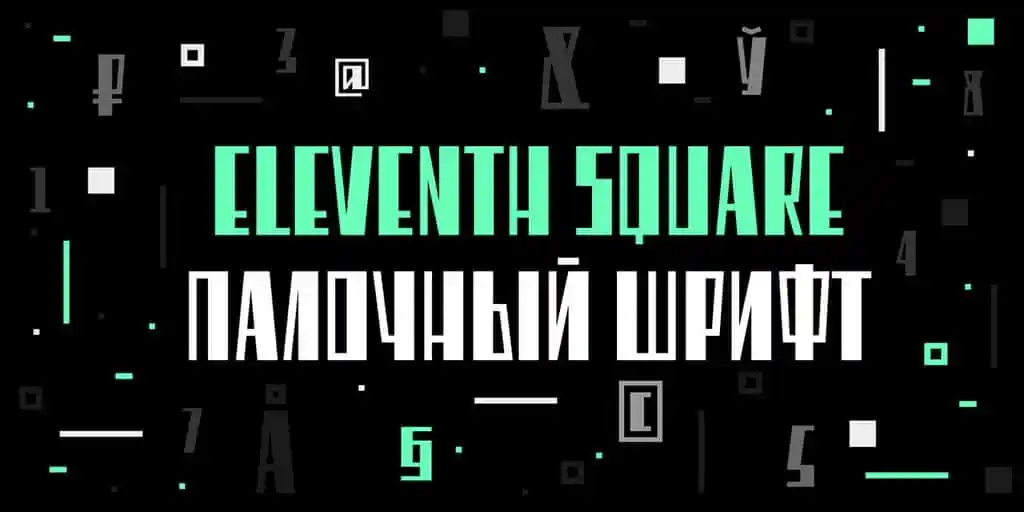
Eleventh Square é uma fonte sans-serif que traz um toque retro com proporções quadradas, criada pelo designer Evgeny Tarasenko para a TypeType School, em São Petersburgo. Este recurso gráfico é projetado pela art-director Ivan Gladkikh e oferece um visual moderno e clean combinando bem em qualquer projeto de design digital. Suas linhas retas e proporções quadradas dão ao texto uma sensação vintage que se mantém atual, enquanto a sua estrutura simples torna-a perfeita para aplicações como designs web ou mídias sociais. A Eleventh Square é uma escolha ótima para quem busca um design minimalista, contemporâneo e claramente definido sem comprometer o charme do design retro.